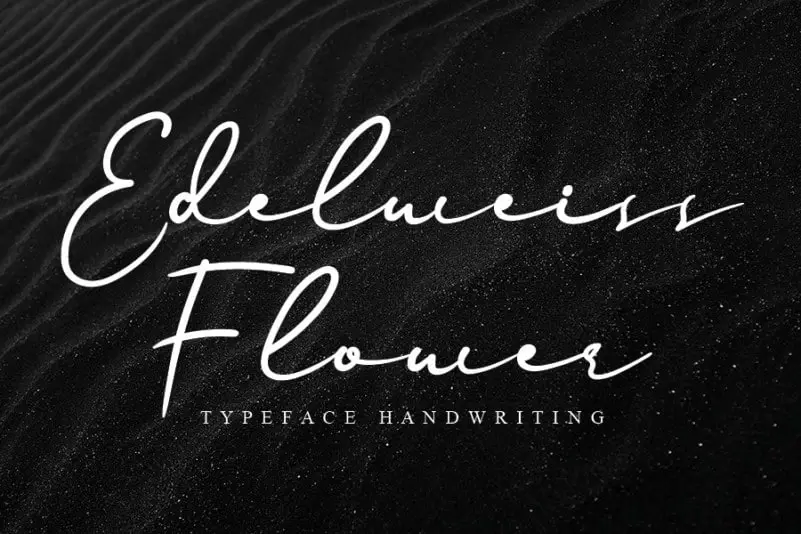
Edelweiss Flower Handwritten Font – Download Grátis
Edelweiss Flower Handwritten Font é uma elegante fonte escrita a mão que transmite relaxamento e fluidez. Suave e mágica, esta fonte está repleta de um jeito único e emocionante. É como se as palavras carregassem uma sensação única e envolvente, prontas para transformar seus conceitos design em algo que realmente toca os olhos. Adicione Edelweiss Flower Handwritten Font aos seus projetos de arte favoritos e permita que a magia aconteça. Este é um recurso visual encantador, perfeito para quem procura uma escrita graciosa e única para adicionar ao seu design. Onde quer que você o use, este é definitivamente aquele em que sua ideia se torna realidade.